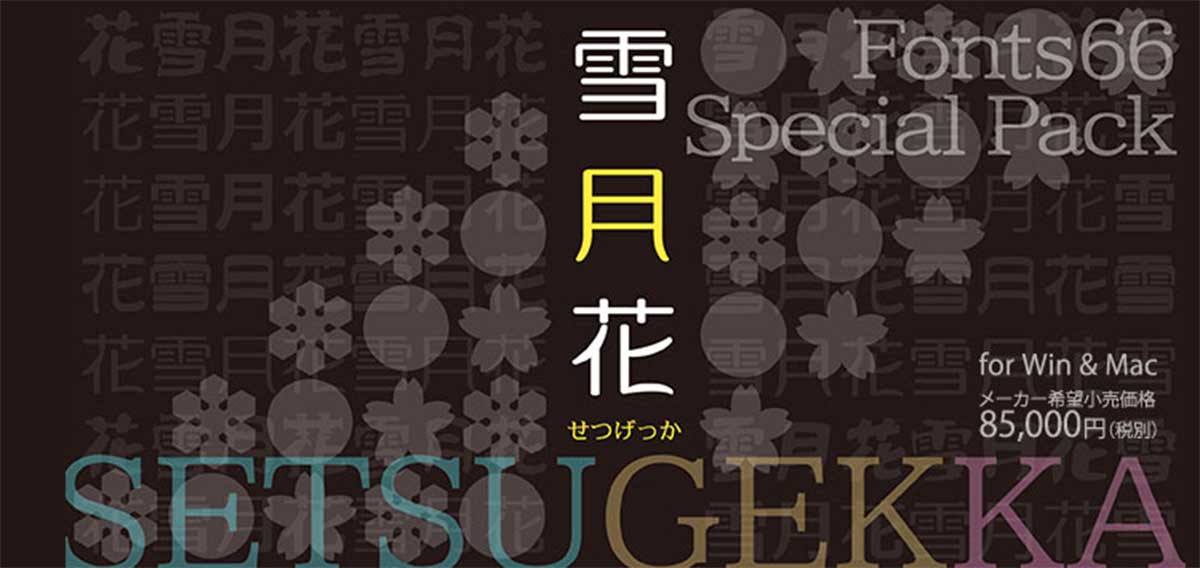
今回は、メイリオの作者鈴木竹治氏のフォントを厳選した「Font66スペシャルパック雪月花」です。味のあるユニークなものから、長文でも使える実用的なフォントまで豊富に収録されています。
「Font66スペシャルパック雪月花」の気になる中身
Font66スペシャルパック雪月花の中身を紹介していきます。
ワッフル/リモーネ
丸みをおびた優しい印象の「ワッフル」と「リモーネ」。それぞれ4種類のウェイトが用意されています。
ワッフルE Petitは、ワッフルEに比べて仮名文字が少し小さめに設定されています。
また、ワッフルU Forteは、ワッフルUに比べて仮名文字を少し太らせています。
ひらがな・カタカナ/記号・半角カナ・全角英数字(プロポーショナル英数)
JIS第一水準漢字・JIS第二水準漢字の一部(256文字)・NEC外字に対応しています。
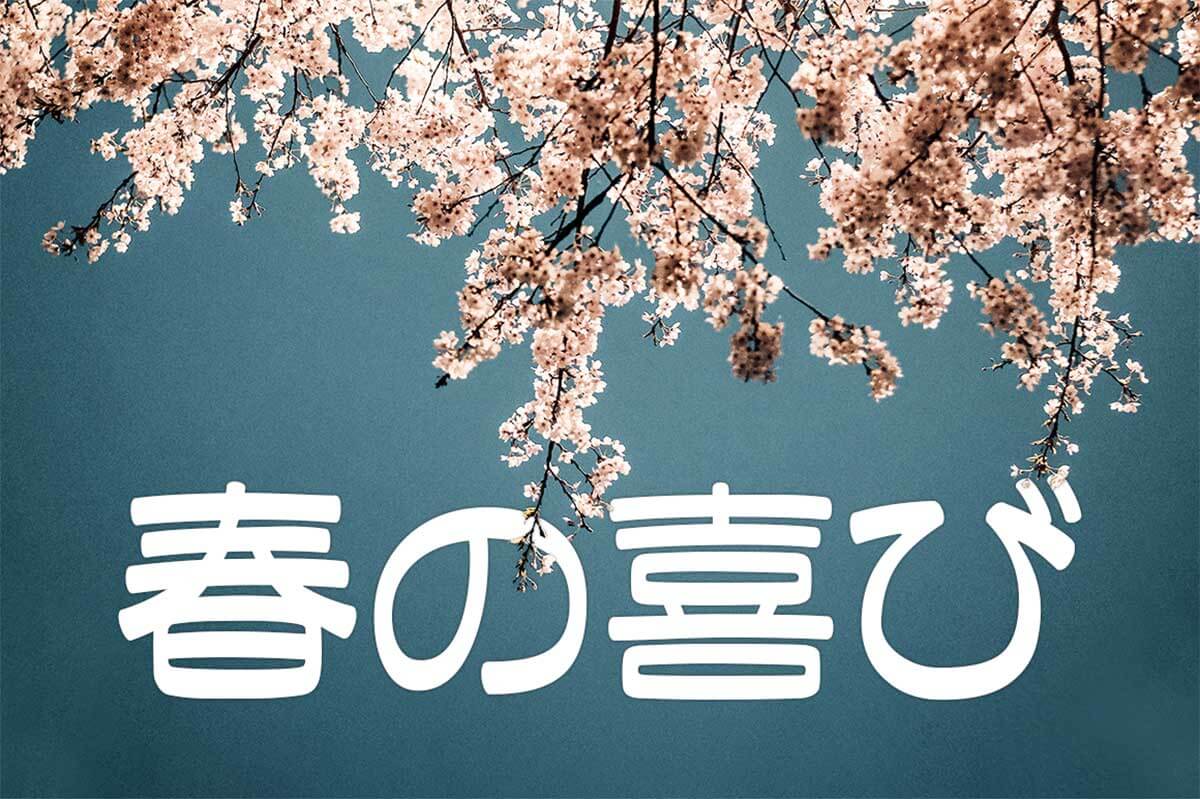
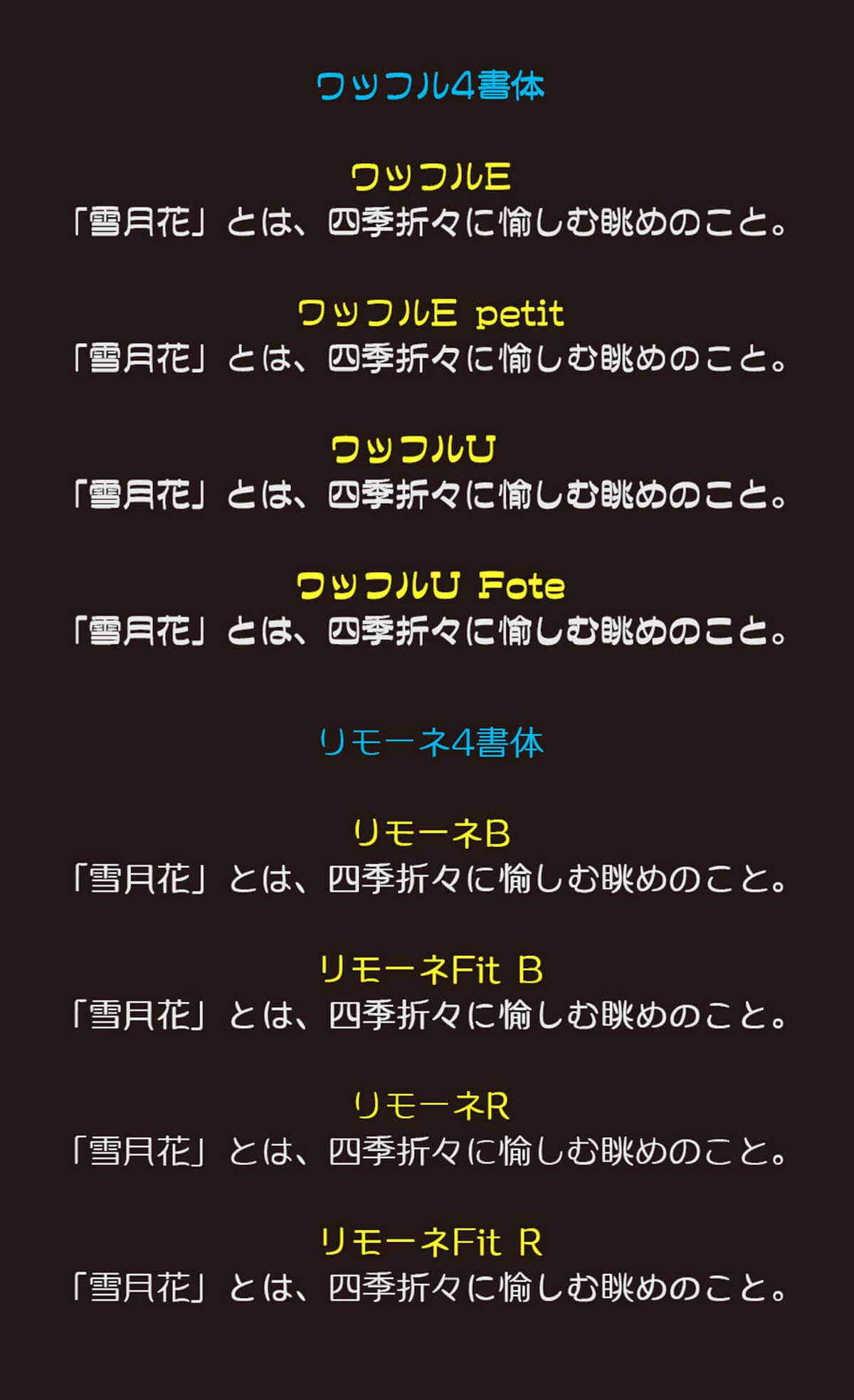
ハンディックH/うんすい/セルフィッシュ/おぼろ
手書き風で味のある「ハンディック」と「うんすい」、使うだけで楽しげな雰囲気が伝わってくる「セルフィッシュ」、どこかはかなげな印象の「おぼろ」。漢字にもしっかり対応しているので、凝ったフォントにありがちな「使いたいのに漢字に非対応」問題から解放されますよ。
ひらがな・カタカナ/記号・半角英数字・半角カナ・全角英数字
JIS X 0201(半角英数字・半角カナ)
JIS X 0208(ひらがな・カタカナ他/第一水準漢字・第二水準漢字の一部(604文字)・拡張文字6字)に対応しています。
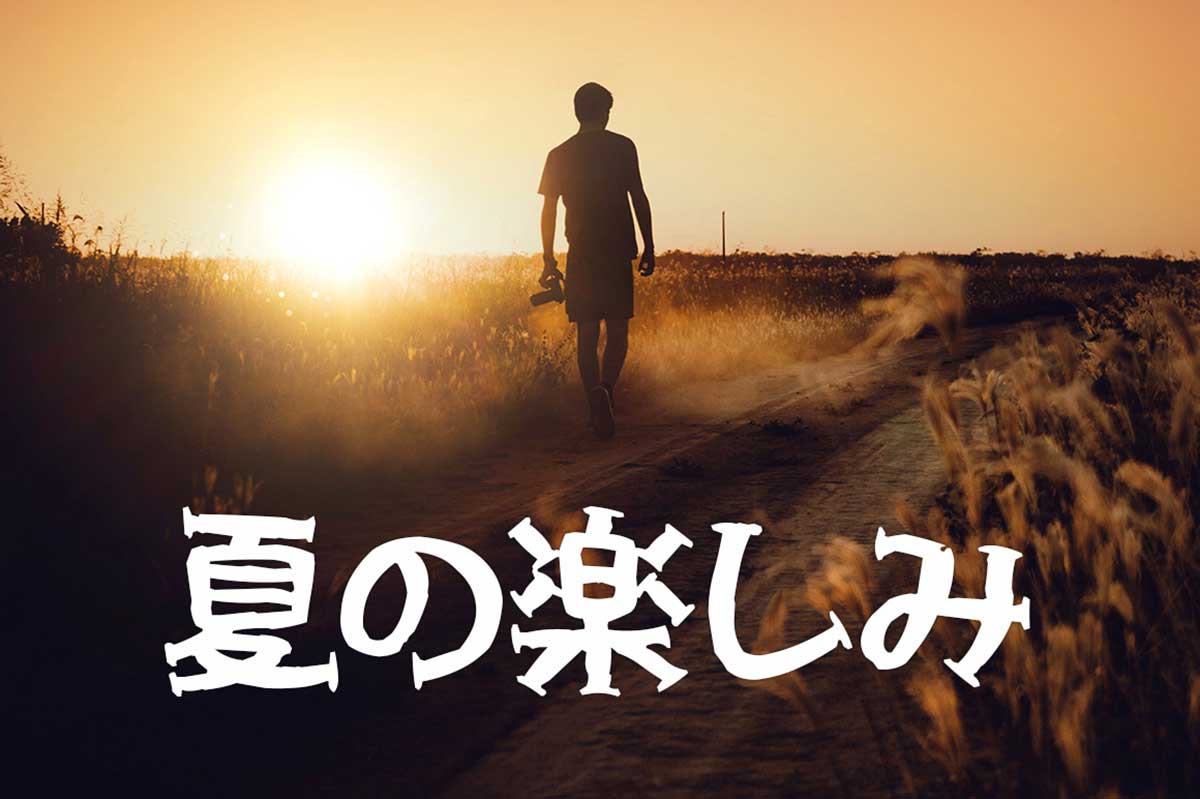
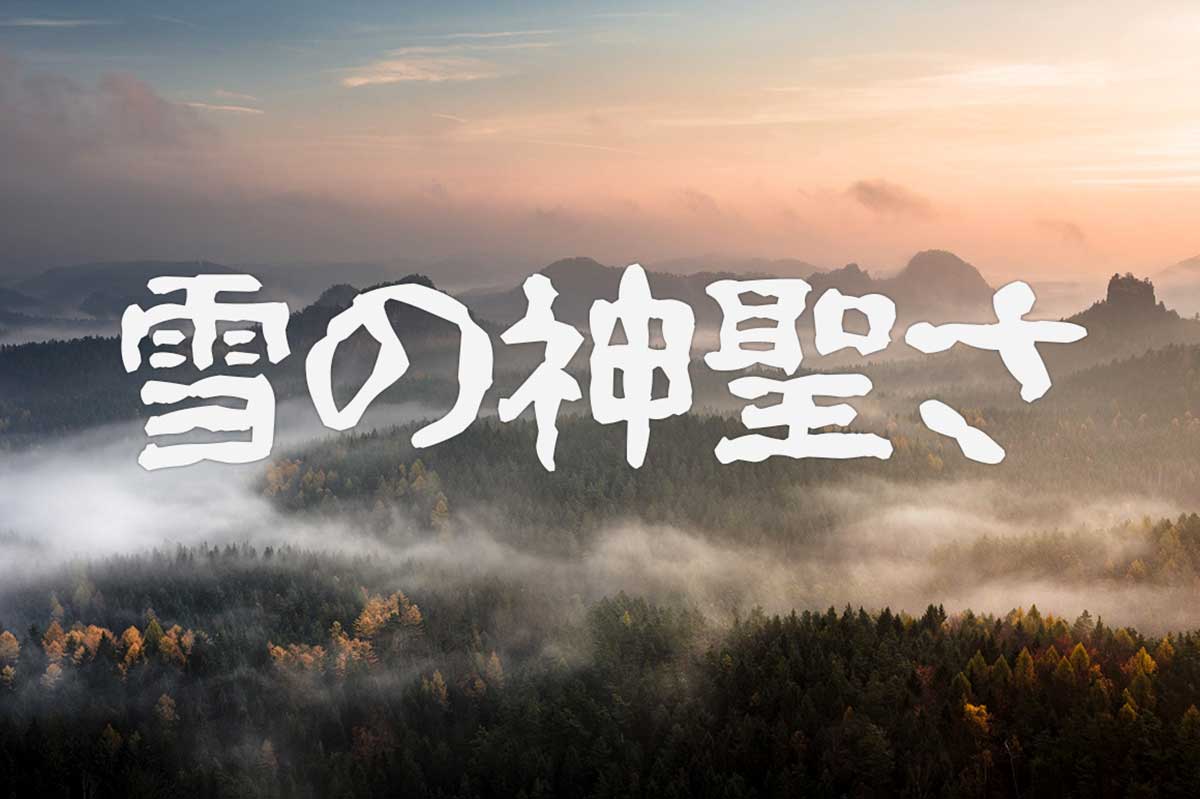
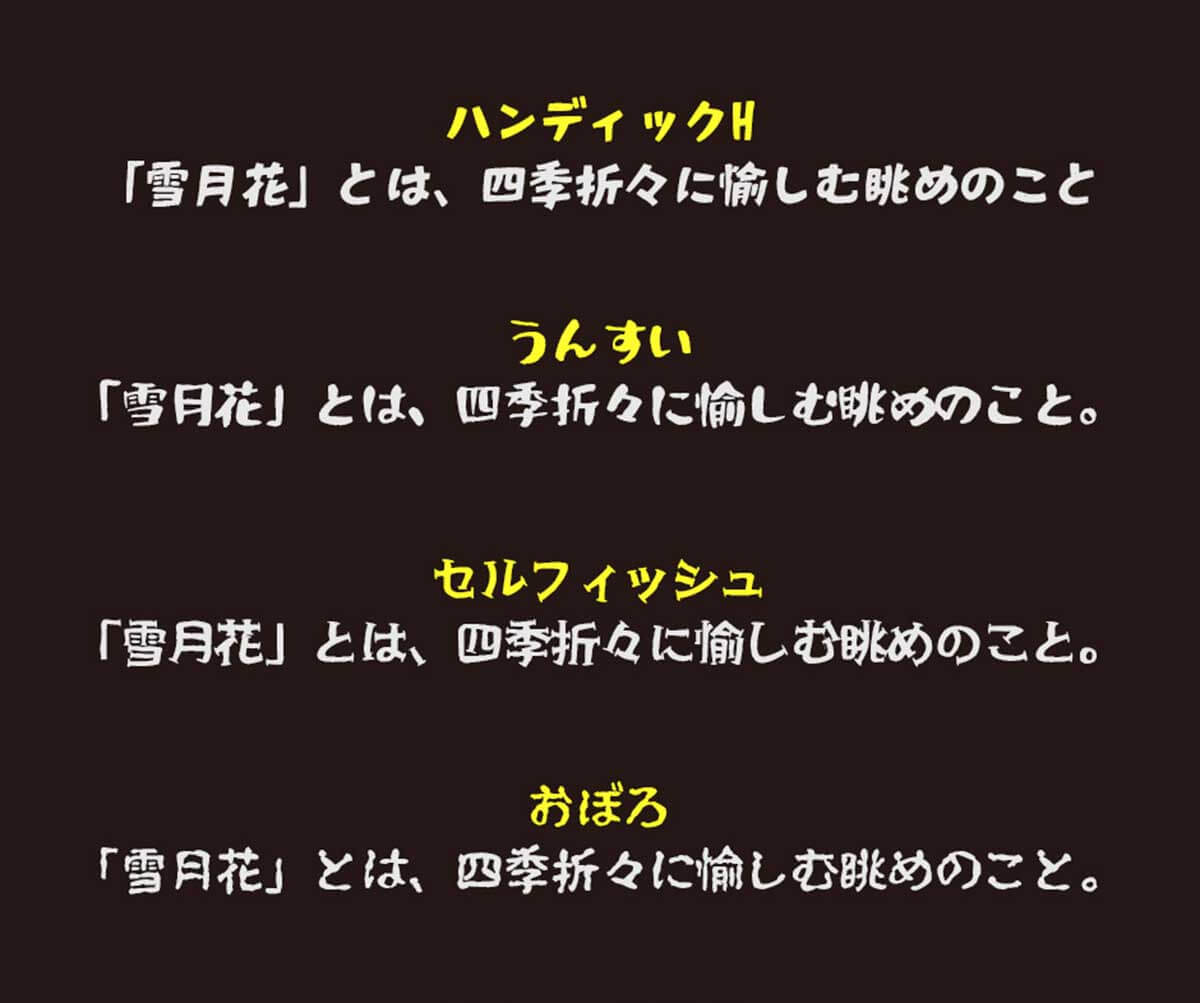
ミンニアム/ユニバーサルライン/スクエア
長文でも読みやすくて実用的な「ミンニアム」、「ユニバーサルライン」、「スクエア」。
ミンニアムは漢字のエレメントとゴシック体的字体を組み合わせたセットと、明朝体仮名「Nexus(ネクサス)」を組み合わせた2つのセットがあります。
ユニバーサルラインは表示用に適した「DSP (ディスプレイ)」、かなが小さめの本文用にデザインされた「BDY(ボディ)」、かながロゴタイプ向きの「LG」の3種類が用意されています。
ひらがな・カタカナ/記号・半角英数字・半角カナ・全角英数字
JIS X 0201(半角英数字・半角カナ)
JIS X 0208(ひらがな・カタカナ他/第一・第二水準漢字を含むJIS基本漢字・拡張文字)
NEC外字に対応しています。